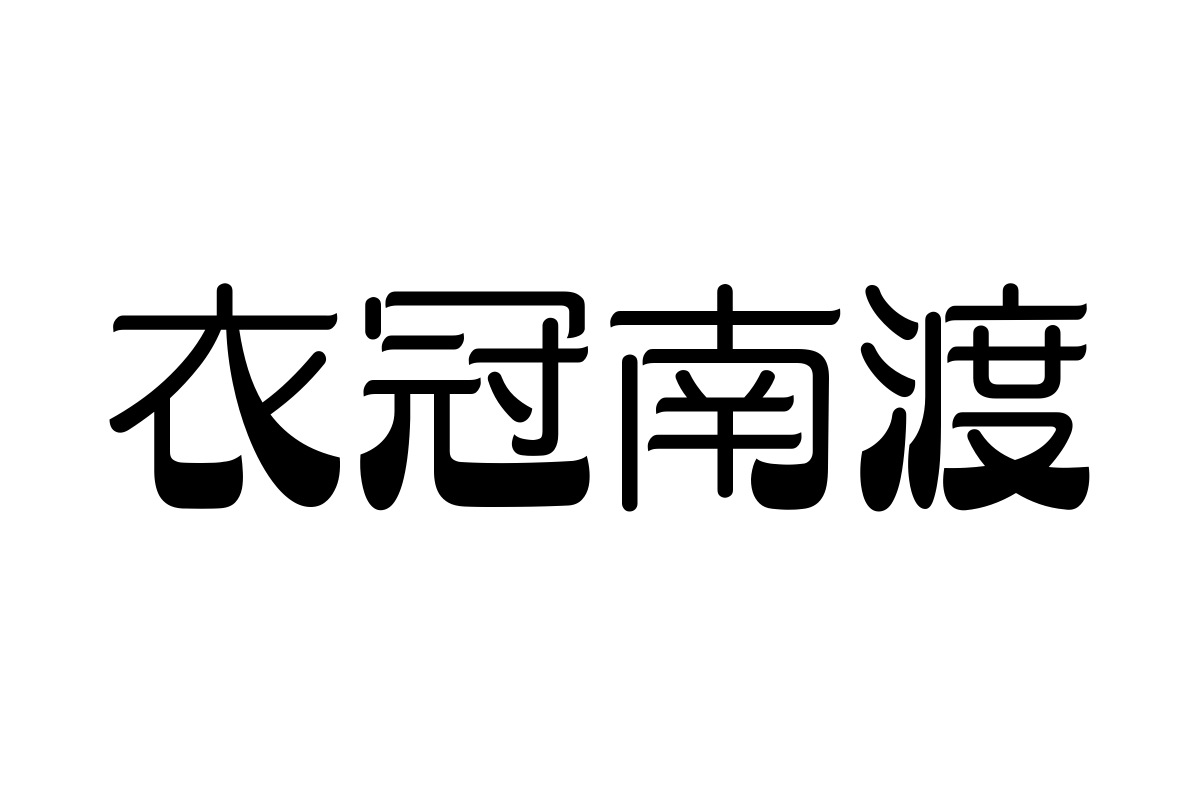
汉仪字研稳态是一款具有现代感和科技感的字体。它的笔画流畅,字形简洁大方,适合用于各种商业、科技、教育等领域的文本设计。这款字体的特点是字形稳定,不会出现变形,适合用于需要长时间阅读的场合。此外,它的笔画粗细适中,既不会过于繁琐,也不会过于简单,能够很好地平衡视觉美感和实用性。总的来说,汉仪字研稳态是一款非常实用的字体,无论是在设计还是在实际使用中都能展现出其独特的魅力。